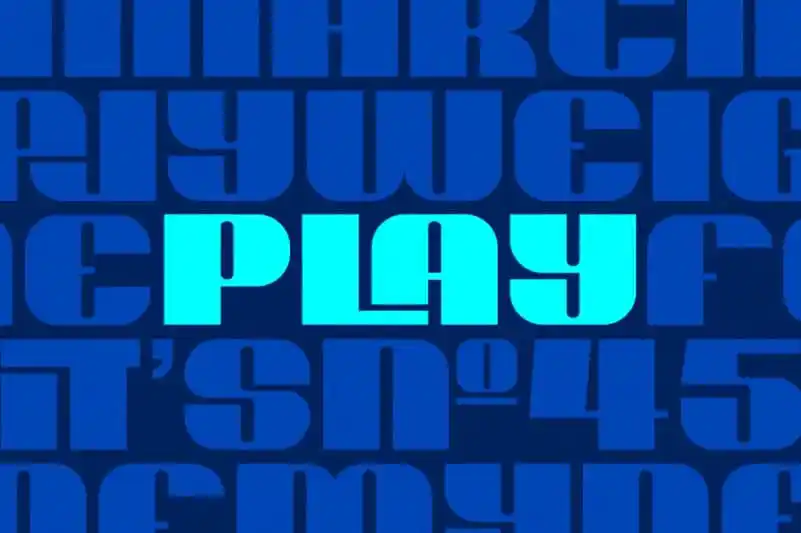
Play Heavy Display Font – Fonte Grátis
Play Heavy Display Font
A Play Heavy Display Font é uma escolha perfeita para quem busca a exuberância dos elementos visuais que definem as ruas e espaços públicos urbanos — sejam os sinárgios ou placas de propaganda, capas de álbuns ou até mesmo marcas gigantes. Inspirada nas formas simples e impactantes desses elementos, essa fonte é resultado do trabalho meticuloso de Don Marciano. Com um design aparentemente simples, a Play Heavy Display Font mantém uma aparência robusta e imponente, capaz de se adaptar a múltiplas temáticas sem deixar nada para trás. Suas linhas retas e limpas oferecem flexibilidade em qualquer aplicação, desde as plataformas digitais até os ambientes físicos. Além disso, o uso inteligente das ligaturas padrão e discretas faz dela uma fonte versátil, ideal tanto para marcas de marca quanto para materiais gráficos de divulgação. Seja em um ambiente urbano ou numa campanha publicitária digital, a Play Heavy Display Font é a escolha perfeita que traduz seus ideais de design em realidade. O equilíbrio entre o exterior arredondado e os ângulos mais finos no interior cria uma identidade visual poderosa, adequada para diversas aplicações gráficas. E com seu estilo robusto e imponente, essa fonte se destaca como uma opção ideal tanto para marcas de marca quanto para materiais publicitários digitais.